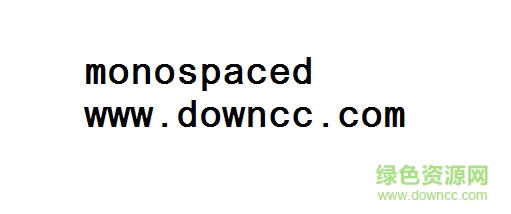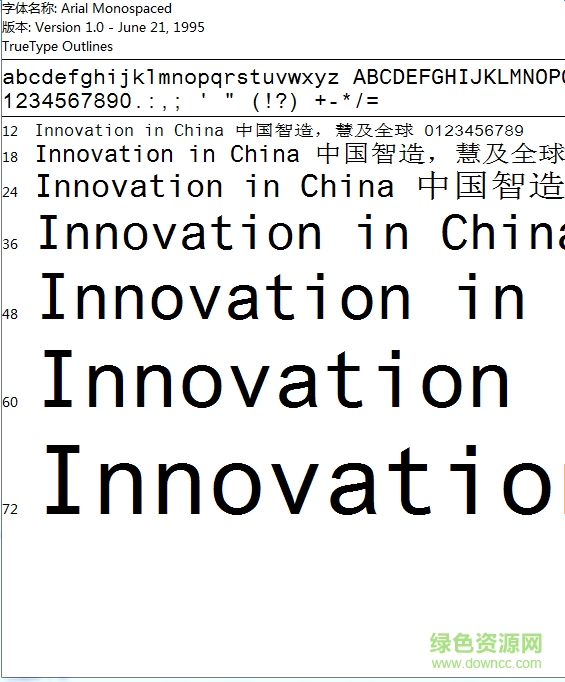
monospaced字體是一款非常正規(guī)的英文字體,該字體筆畫一絲不茍,得體大方,十分好看,整體給人非常正式的感覺,更多好看字體下載盡在綠色資源網(wǎng)!
monospaced字體是一款應用于藝術設計方面的簡體英文字體,細節(jié)表現(xiàn)完整,且字庫完整,可以廣泛應用于名片設計、新聞媒體、宣傳海報、ppt、影視制作以及內(nèi)容用字等領域。